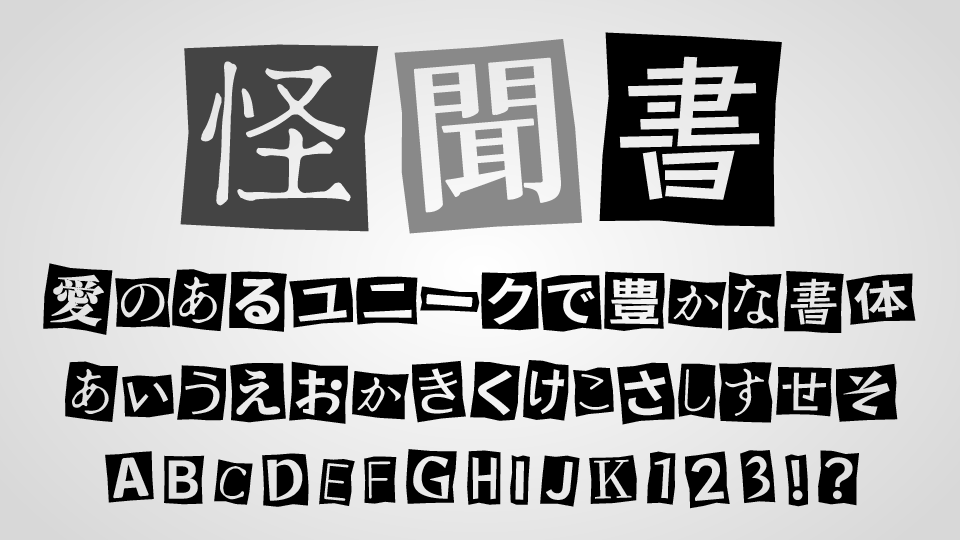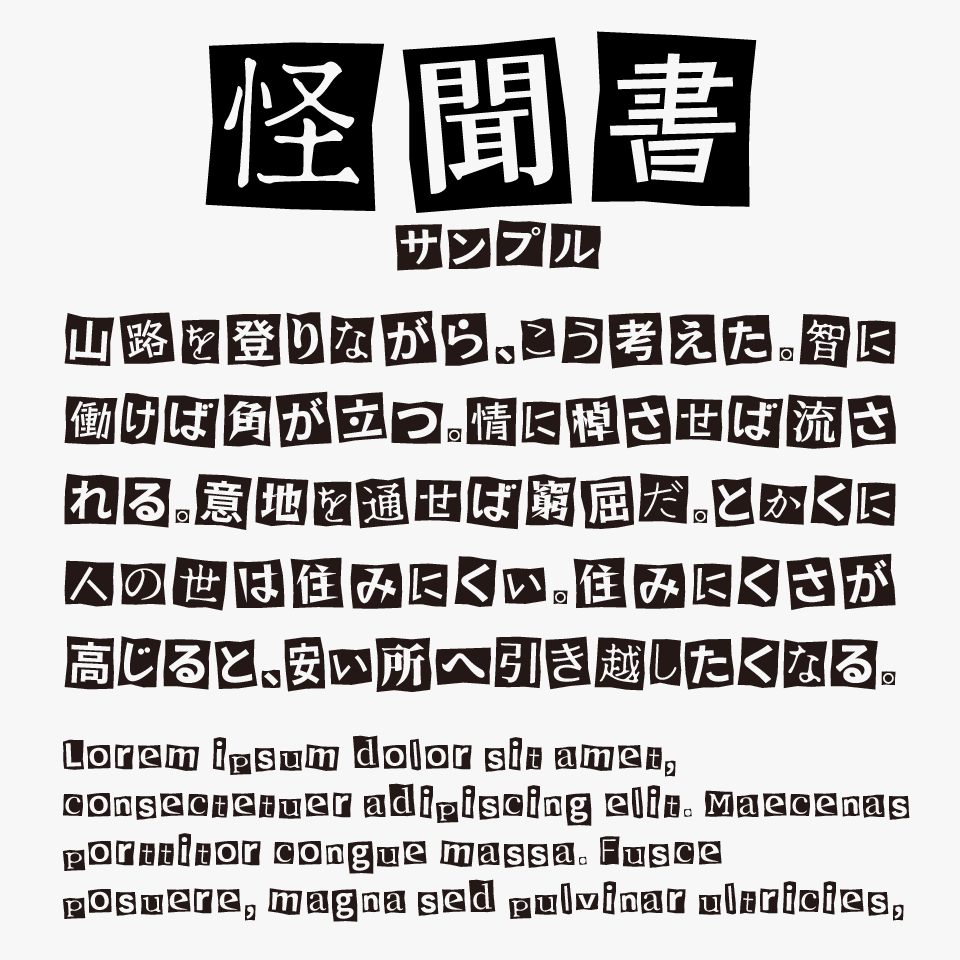
怪聞書
怪聞書フォントは、さまざまなフォントを混ぜつつ新聞を無造作に切り抜きしたような背景が付いている怪文書を彷彿させるユニークなデザインフォントです。
文字ごとに異なるサイズ感や配置バランスによって、整っていない不気味さと手作業感を絶妙に表現しているフォントです。黒背景に白文字を乗せたような強いコントラストも特徴で、ひと目で“怪文書らしさ”を感じさせる独特の存在感がとってもユニークで面白いです。
ホラー系のサムネイルやミステリー演出、都市伝説風デザインなどと相性が良く、文字を並べるだけで緊張感のある空気を作り出せます。
同様に、背景付きや複数フォントを混ぜたようなデザインフォントと比較してみると、怪聞書フォントは不気味な雰囲気”を感じさせてくれるフォントです。
比較フォントは「怪盗予告ゴシック」「MPRばるーん」「ピグモ」と使用していますが、どのフォントもとてもステキななので、あわせてチェックしてみてください。